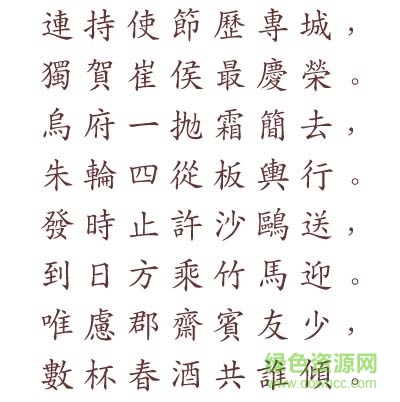
長(zhǎng)城中楷體繁是一款筆畫(huà)中等粗細(xì)的楷體繁體字。該字體完美結(jié)合了楷體的方正特點(diǎn),讓你每天都能能加喜歡中華字體,喜歡就來(lái)綠色資源網(wǎng)下載吧!
應(yīng)用于平面設(shè)計(jì)方面的繁體中文字體。該字體端正大方得體,線條纖細(xì),整體效果非常出色,可廣泛應(yīng)用于平面設(shè)計(jì)、簽名設(shè)計(jì)、廣告設(shè)計(jì)、報(bào)紙雜志、正文標(biāo)題等領(lǐng)域,